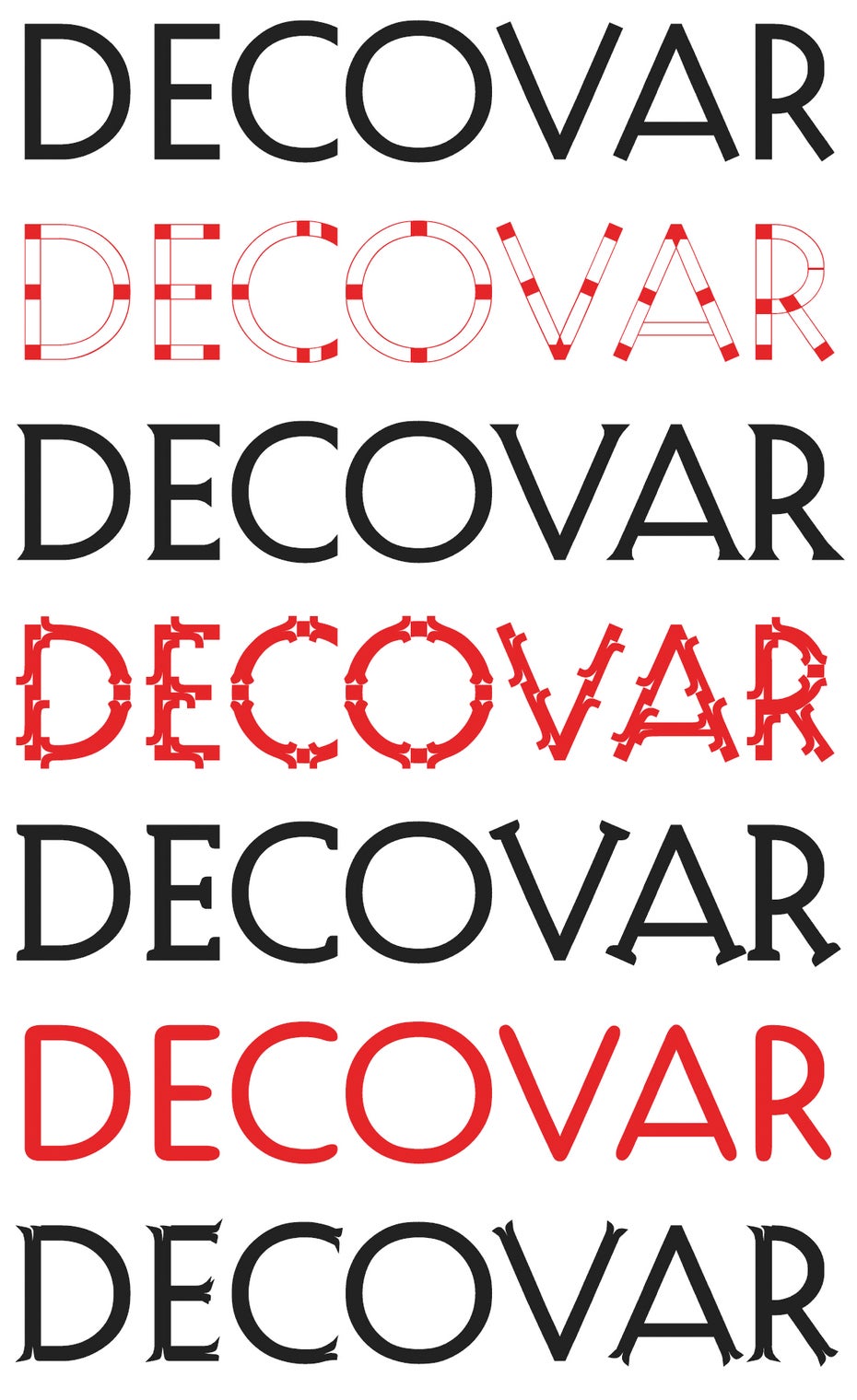
Variable Fonts: Das neue Schriftformat erobert das Web
In den Anfangszeiten der Webfonts waren Webdesigner schon damit zufrieden, endlich Alternativen für Arial, Georgia und Co. an der Hand zu haben. Aber recht schnell wuchs der Anspruch, auch im Web abwechslungsreiche Typografie auf Printniveau anwenden zu können: Mehr und mehr Schriftschnitte wurden eingebunden, um typografische Vielfalt zu erzeugen. Doch mit jedem Schriftschnitt musste eine weitere Datei geladen werden, was die Ladezeiten in die Höhe schnellen ließ. Genau hier setzen heute variable Fonts an. Sie sind mit dem Ziel der Datenkomprimierung entwickelt worden, bieten aber darüber hinaus noch weitere Vorteile.
Was sind variable Fonts?
Eine Schriftart gibt es in der Regel mit verschiedenen Schriftschnitten oder Schriftstilen beziehungsweise Strichstärken – etwa „Light“, „Regular“, „Bold“ – oder Schriftbreiten wie „Condensed“ oder „Extended“. Jeder dieser Schriftstile wird vom Schriftdesigner festgelegt und in einer separaten Datei gespeichert. Je nach Umfang der Schriftart können hier natürlich viele Einzeldateien entstehen, was gerade im Web aufgrund längerer Ladezeiten nicht von Vorteil ist. Dieses Problem haben Adobe, Apple, Google und Microsoft erkannt und 2016 zusammen mit weiteren Experten das Opentype-Format um „Opentype Font Variations“, bekannt als „variable Fonts“, erweitert.
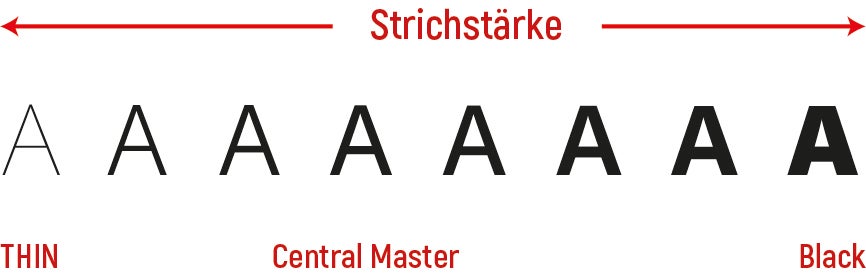
Variable Fonts verknüpfen den Basisschriftschnitt (Central Master) mit den Extremwerten einer Schrifteigenschaft, beispielsweise mit „Thin“ und „Black“. So entsteht eine Achse, entlang derer die Schriftstärke stufenlos interpoliert werden kann. (Abbildung: Christoph Zillgens)
Mit diesen variablen Fonts ist es jetzt möglich, verschiedene Schriftstile einer Schrift in einer einzigen Datei zu vereinen. Einzelne Schriftschnitte werden dabei nicht in separate Dateien ausgelagert, sondern über verschiedene Achsen definiert. Ein Basisschriftschnitt, Central Master genannt, wird dabei mit Extremwerten einer Schrifteigenschaft, beispielsweise „Thin“ und „Black“, verknüpft. So entsteht eine Achse, entlang derer die Strichstärke stufenlos interpoliert werden kann. In der Opentype-Spezifikation sind fünf Standardachsen hinterlegt: für die Strichstärke, die Schriftbreite, die Neigung, die optische Größe sowie die Kursive. Allerdings ist es nicht immer möglich, die Kursive in die gleiche Datei zu integrieren, denn oftmals werden bei einer richtigen Kursiven viele Zeichen komplett neu gezeichnet. Sie lassen sich somit nicht aus dem aufrechten Schnitt interpolieren.
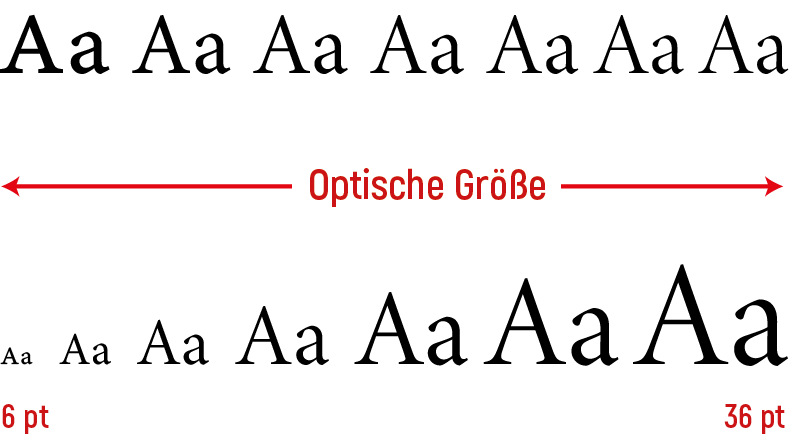
Alles in nur einem Font: Macht man die Schrift per Schieberegler kleiner oder größer, wird automatisch die richtige optische Größe gewählt. (Abbildung: Christoph Zillgens)
Die Standardachsen müssen nicht zwangsweise alle belegt sein. Zusätzlich können auch weitere Achsen für Serifenform und -länge, Kontrast, Konturen und sonstige Ausprägungen angelegt werden. Der Kreativität sind keine Grenzen gesetzt. Wer eine aktuelle Version der Creative Cloud von Adobe nutzt, kann in Illustrator oder Photoshop verschiedene Schriften wie Acumin, Minion oder Myriad als variablen Font testen. Diese sind mit dem Zusatz „Variable Concept“ gekennzeichnet und lassen sich über das Schriftmenü aufrufen. Die verschiedenen Achsen lassen sich dann über Schieberegler steuern. In CSS ist es möglich, über die Eigenschaft font-variation-settings die verschiedenen Achsen anzusteuern und die Schriftdarstellung zu beeinflussen. Wie das geht, zeigt der nächste Abschnitt.
Variable Fonts anwenden
Variable Fonts sind zurzeit ein experimentelles Feature, das noch nicht zuverlässig browserübergreifend funktioniert. Dennoch liegt die Browser-Unterstützung deutschlandweit aktuell schon bei rund 65 Prozent. Dass einem produktiven Einsatz nichts im Wege steht, zeigt die Website der Webtypografie-Konferenz Ampersand (2018.ampersandconf.com), die von variablen Fonts schon Gebrauch macht.
(github.com/google/woff2), mit dem die Umwandlung in Woff2 durchgeführt werden kann.
Der oben genannte Code bindet den variablen Font ein, der von unterstützten Browsern angewendet werden kann. Dies sind – Stand Juli 2018 – die aktuellen Versionen von Edge, Chrome und Safari (ab MacOS 10.13). Firefox wird mit der Version 63 nachziehen.
Nun lässt sich die Schrift wie gewohnt über die font-family Eigenschaft dem gewünschten HTML-Element zuweisen. Über die Eigenschaft font-variation-settings können die verschiedenen Achsen angesprochen und mit Werten versehen werden. Wie bereits skizziert, sind fünf Standardachsen hinterlegt, die mit jeweils vier Zeichen langen, kleingeschriebenen Tags im CSS bezeichnet werden:
Achse | Name | CSS-Tag |
---|---|---|
Strichstärke | Weight | wght |
Schriftbreite | Width | wdth |
Kursive | Italic | ital |
Neigung | Slant | slnt |
Optische Größe | Optical Size | opsz |
Diese Tags können mit Werten gepaart werden und so die gewünschte Schriftdarstellung anzeigen lassen. Im folgenden Beispiel entspricht der verwendete Wert 700 dem Schriftschnitt „Bold“:
html{ font-family: 'Amstelvar'; font-variation-settings: "wght" 700; }
Weitere Achsen können kommagetrennt ergänzt werden. Liegen individuelle Achsen vor, werden diese mit Großbuchstaben ergänzt. Die Schrift Amstelvar verfügt zum Beispiel über eine Achse namens „Grade“, welche die Strichstärke dünner oder fetter macht – ohne dabei die horizontale Ausdehnung der Schrift zu verändern:
Fazit
Variable Fonts bieten neben Einsparungen in der Dateigröße viele weitere Vorteile wie Feinjustierung der Webtypografie oder Anpassung an verschiedene Gegebenheiten wie Displaygröße und -auflösung. Bis Ende 2018 werden alle großen Browser variable Fonts unterstützen. Und wenn Schriftgestalter und -anbieter diese dann mit sinnvollen Preis- und Lizenzmodellen bereitstellen, steht der Kreativität nichts mehr im Wege. Allerdings sollten Webdesigner die neuen Freiheiten auch mit Bedacht einsetzen. Denn zu viel Spielerei mit variablen Fonts wird Website-Besucher eher ablenken, als ihnen nutzen.